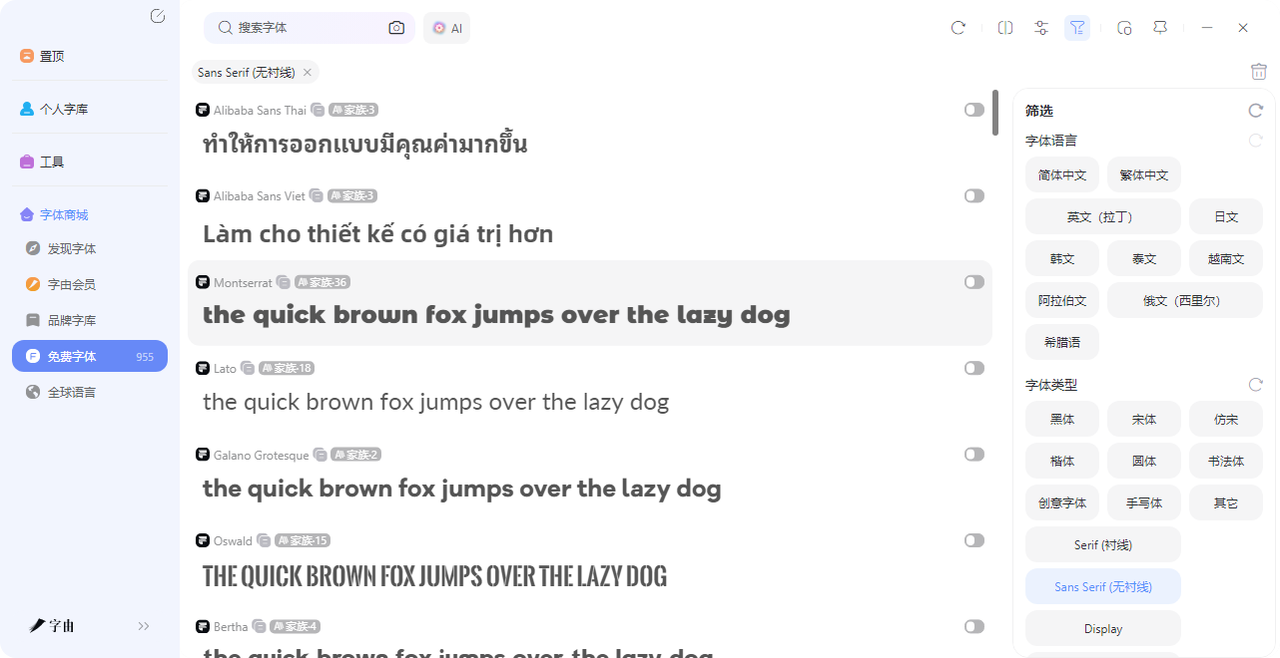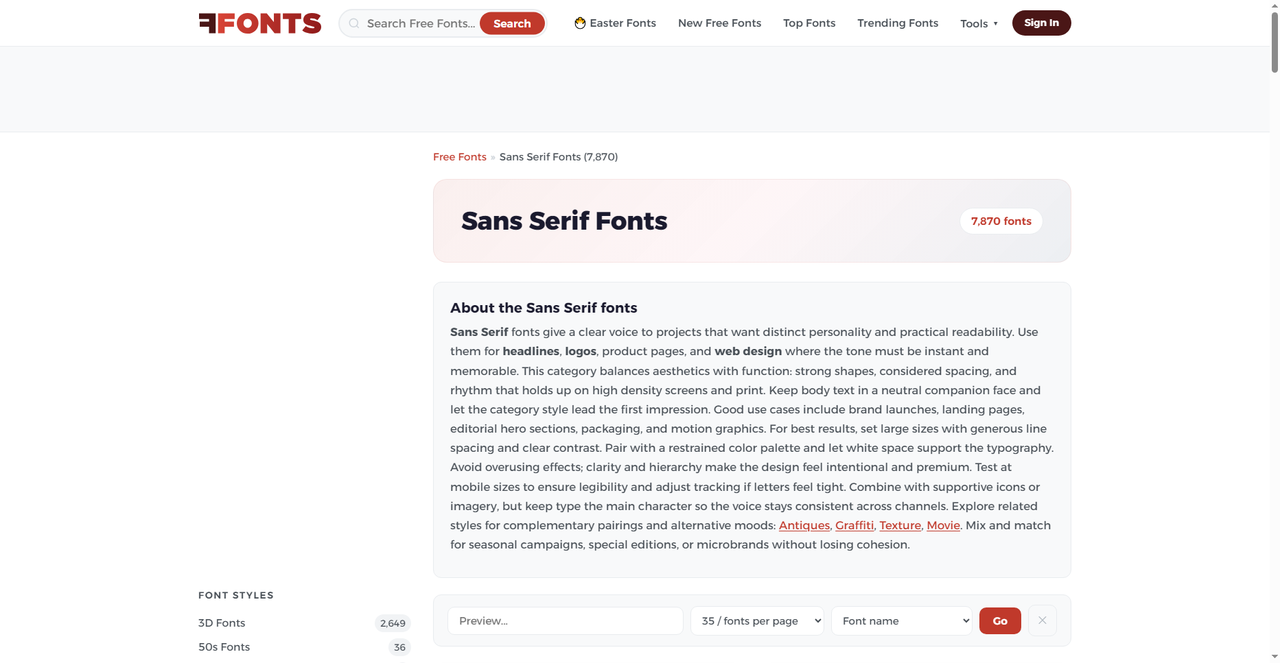
等线字体哪里找?5个免费下载无衬线字体网站推荐
有时候高级的设计的关键是一个简约大气的字体,而等线字体就是很好的选择,也就是设计师常说的无衬线体。简洁、现代、好认,不管是大标题还是小正文,放上去都不违和。但问题是:等线字体下载去哪找靠谱的?今天我就会为大家在本篇文章整理 5 个免费等线字体下载的网站。看完这篇希望你能够有所收获!
字由是目前国内设计师用得最多的字体管理工具之一。它不是那种只有单一功能的字体下载网站,如果你用了客户端以后,你就会发现里面的字体可以直接“激活”到你的设计软件里,不用安装,不用重启。这也是字由作为字体工具非常方便的一个优点,除此之外,字由里有 955 款免费的无衬线字体可供选择。这个数量,比很多专门的英文字体站都多。接下来我会教大家如何在字由里找到等线字体:
首先我们要用到筛选功能,字由的筛选维度做得非常细。客户端里能看到有这些筛选项:
- 字体语言:简体中文、繁体中文、英文(拉丁)、日文、韩文、泰文、越南文、阿拉伯文、俄文、希腊语……你想找哪种语言的无衬线体,直接勾选就行。
- 字体类型:黑体、宋体、仿宋、楷体、圆体、书法体、创意字体、手写体、其它。无衬线体主要对应“黑体”这一分类。
- 衬线/无衬线:Serif(衬线)、Sans Serif(无衬线)、Display(展示字体)。这里选了 Sans Serif。
也就是说,你不需要在一大堆字体里慢慢翻。打开字由客户端,在免费字体里选“Sans Serif”,再确保“免费”开关是打开的,就能看到所有适合中英文混排的免费无衬线体。整个过程不到 10 秒。
然后我会推荐一些我觉得好用的等线字体:
- Proza Libre:开源无衬线体,笔画清晰,适合正文排版。
- Baloo 2:圆润风格的无衬线体,适合儿童产品或轻松氛围的设计。
- melete:学术感强一些的无衬线体。
- Passion One:粗体无衬线,适合做冲击力强的大标题。
- HostGrotesk:现代风格的无衬线字体家族。
- Economica:字形偏窄,适合空间有限但需要清晰展示的场景。
- D-Din:经典的工程风格无衬线体,适合技术文档或工业设计。
2、Sans Serif Fonts
第二个要介绍的网站是一个专门收录无衬线字体的资源站。页面顶部有一段关于无衬线字体的介绍:“Sans Serif fonts give a clear voice to projects that want distinct personality and practical readability.” 意思就是无衬线字体既有辨识度又好读。
这个站最大的特点是分类极其细致。页面中间有一个长长的“FONT STYLES”列表,我数了一下,有四五十种分类,绝对够用。
3、FontSpace
FontSpace 的 Sans Serif 分类下的内容也很丰富,而且FontSpace 是一个老牌免费字体下载站,体量大、用户多。我比较推荐的几款是:
- Helvena Grotesk Font:“a modern and clean grotesk sans serif typeface crafted for bold branding, brand identity, and editorial design.”
- Latinka Font:包含 18 种样式的字体系列
- Inspire Impact Font:“an elegant and familiar sans serif font”
- Kind Sans Font:“a modern and cool sans serif font that contains 18 styles”
每款字体都配有预览图和简短的风格说明。FontSpace 的特点是收录的字体质量比较稳定,不像一些小站那样良莠不齐。
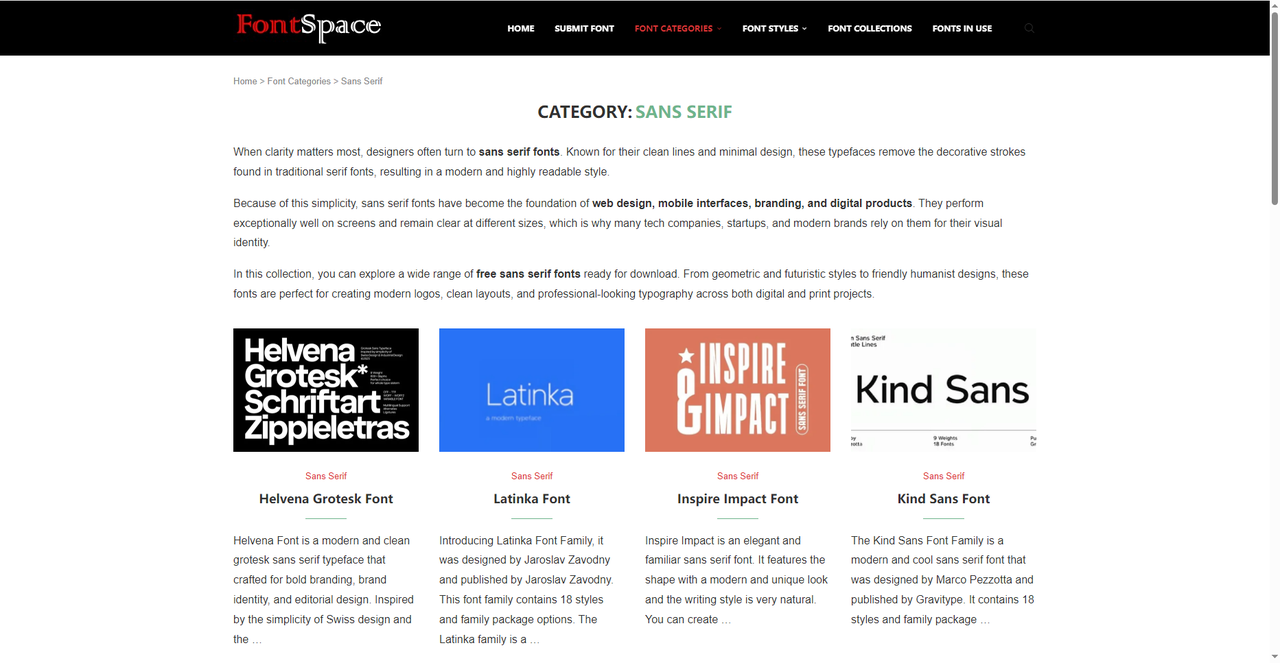
4、CUFON Fonts
这个网站布局比较紧凑,左侧有筛选维度,而且筛选方式挺特别的。它按照“这款字体有多少种样式”来分类——样式越多,说明字体系列越完整,从细到粗都有。如果你想找一个完整的字体系列(比如要有 Light、Regular、Medium、Bold、Black 等多个字重),可以直接选“8+ Styles”或者“10+ Styles”。页面上方还有几个排序选项:Newest(最新)、Hot Today(今日热门)、Popular(最受欢迎)、Variable(可变字体)。你可以按这些维度来发现字体。
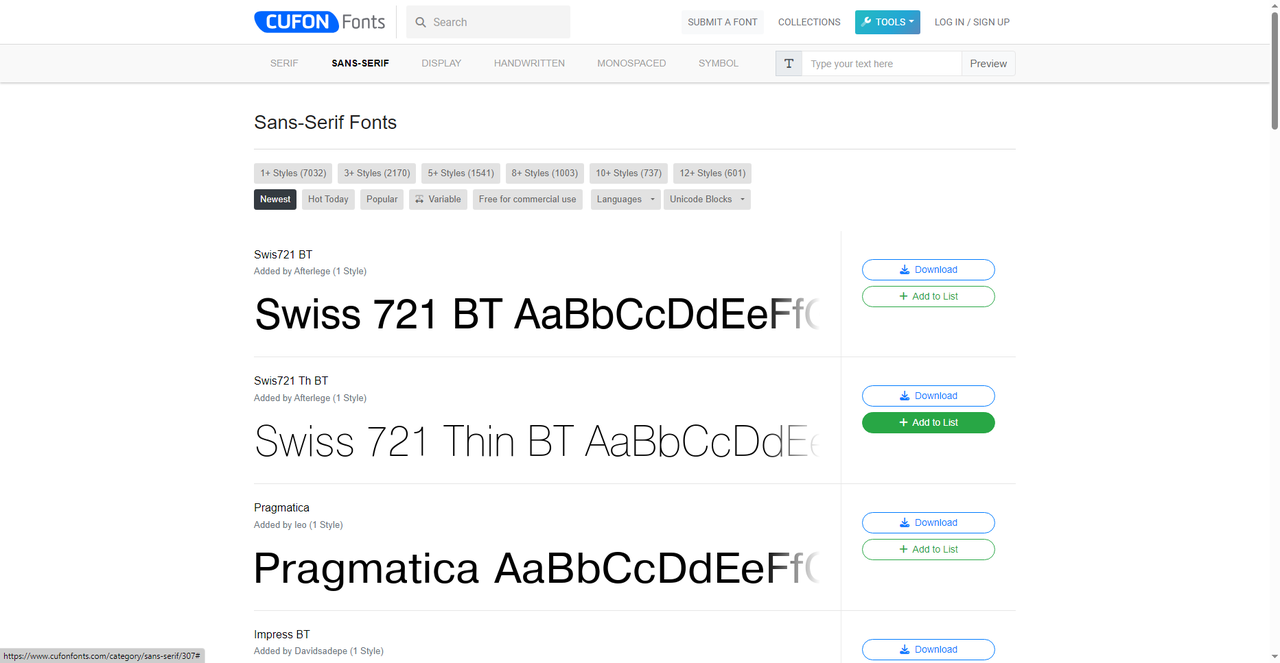
5、Adobe Fonts
Adobe 的界面设计十分简洁,而且提供的字体资源都非常经典,我常用的大概有以下几款:
- Microsoft Sans Serif:微软系统自带的经典无衬线体,只有 1 款字体。这款字体在 Windows 系统里本来就有,不需要下载。但如果你在其他平台用,可以在这里获取。
- FF Dax:来自 FontFont 厂牌,包含 42 款字体。这是一个很庞大的字体系列,适合专业设计项目。
- Range Sans:一款当代无衬线字体家族,描述写的是“Contemporary type family with a touch of angularity and easy interchanging of styles.” 带有一些棱角感,样式之间可以灵活替换。
这里的特点是展示了一些可变字体(Variable Fonts)。可变字体是字体技术的新方向——一个文件里包含了字重的所有变化,你可以用 CSS 精确控制粗细,而不需要加载多个字体文件。
无论你是 UI 设计师、PPT 高手还是偶尔做做海报的运营,等线字体下载的需求是肯定的,而字由把这 955 款免费无衬线体整理得明明白白,还配了一键激活功能,再加外另外 4 个国外网站可以作为补充,找一些更小众、更风格化的无衬线字体。如果喜欢的话可以都试试!